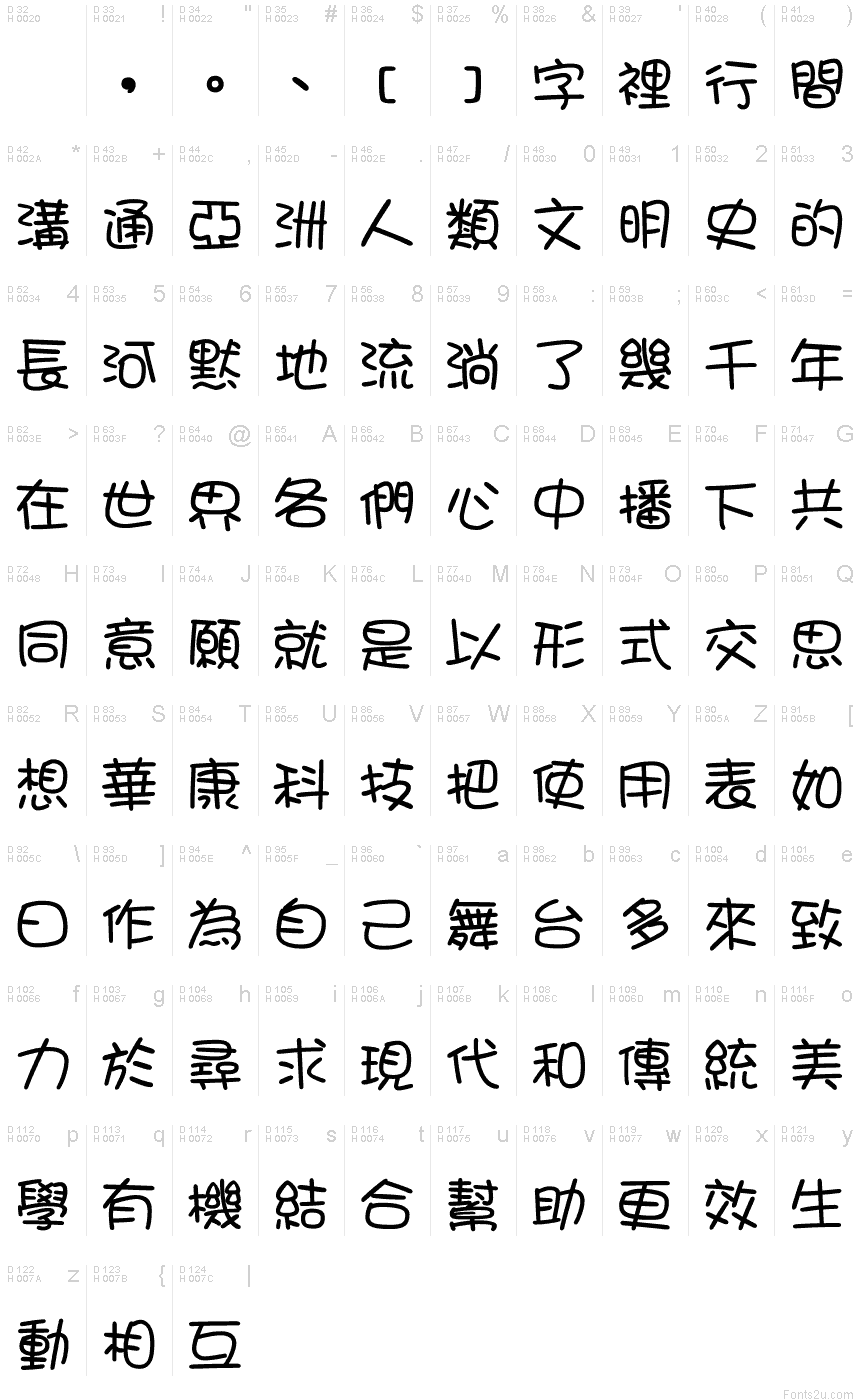
DF Girl 1B von DynaLab ist eine kostenlose chinesische Handschrift-Schriftart mit dem entspannten Flair von Pinsel- oder Marker-Schriftzügen. Die Striche wirken breit, abgerundet und leicht unregelmäßig, wodurch die Schriftzeichen eher freundlich und lässig als formell wirken, dabei aber den ausgewogenen, aufrechten Rhythmus alltäglicher Beschriftungen beibehalten.
Sie passt ideal auf Verpackungen, Speisekarten in Cafés, Plakatüberschriften, Buchtitel und Event-Grafiken, wo chinesischer Text eine menschliche Note braucht. Als kostenlose Schriftart eignet sie sich auch hervorragend für kurze Schlagzeilen, Titelkarten und einfache Logos, da die weichen Strichenden die Buchstaben lebendig wirken lassen, ohne dabei überladen zu sein.